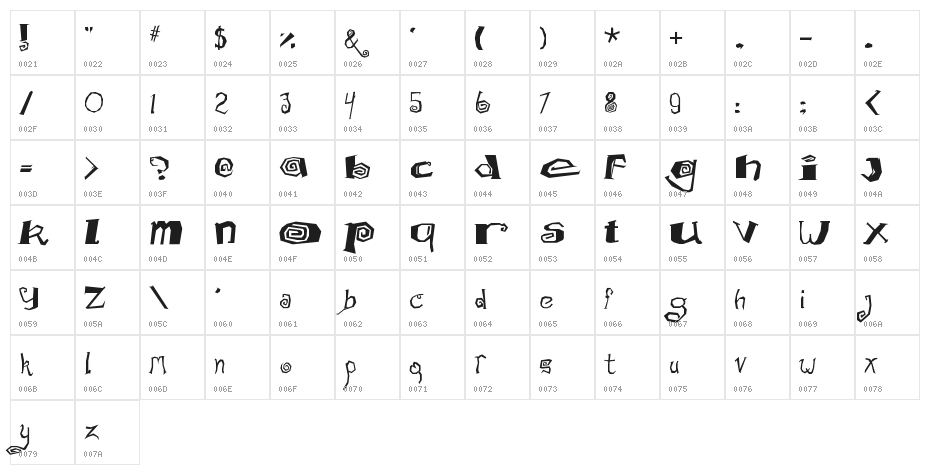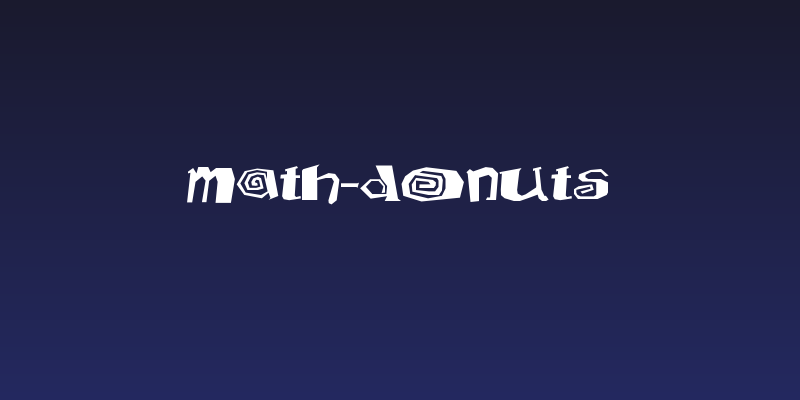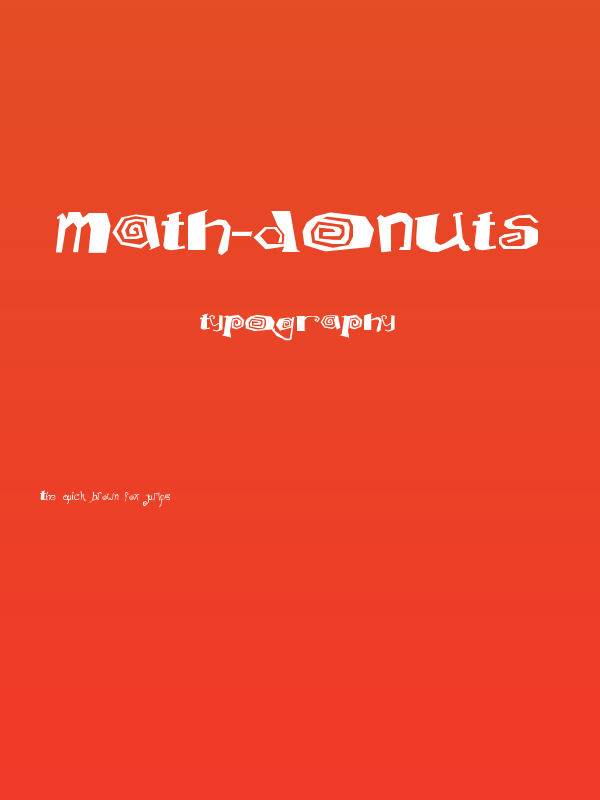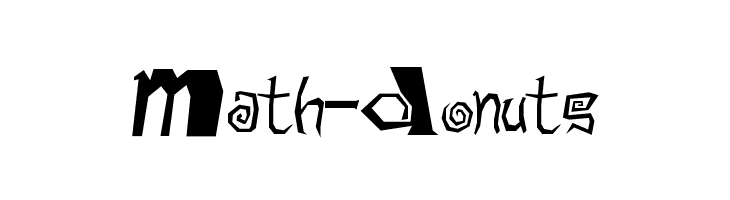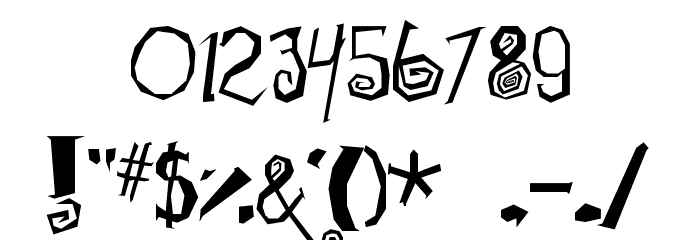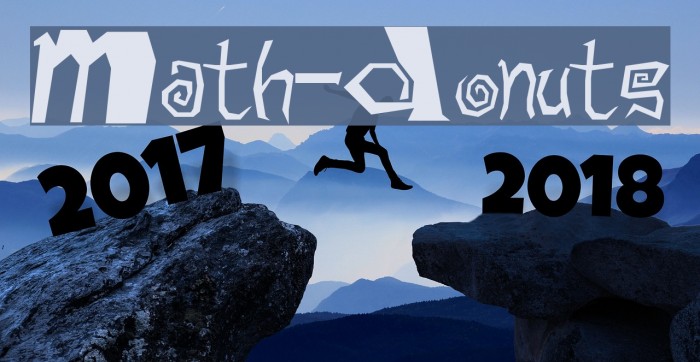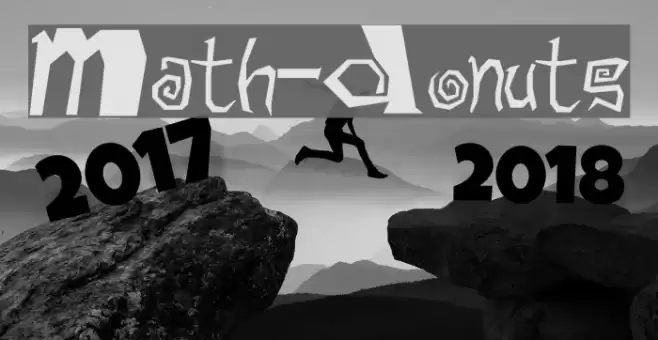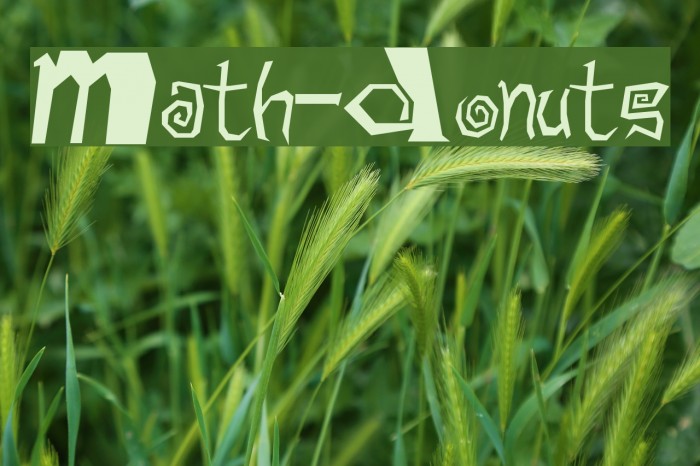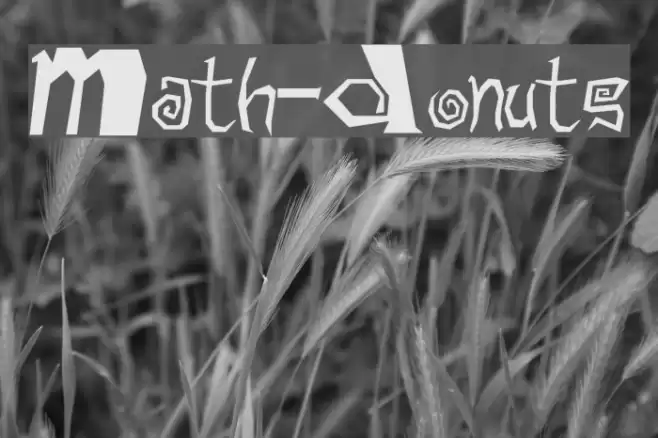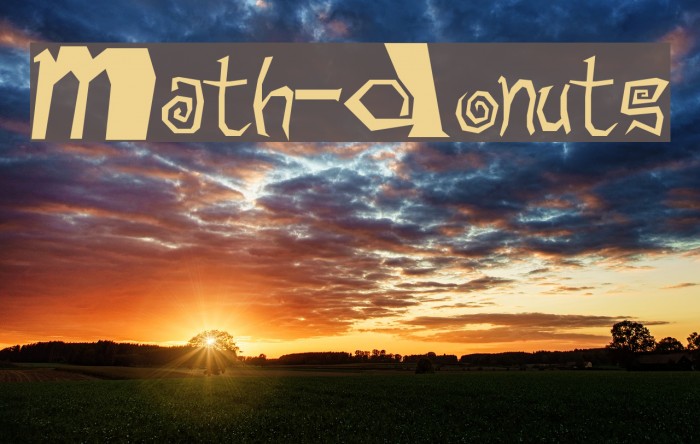
Math-Donuts Font
| Style général | Playful, Quirky, Artistic |
| Projets proposés | Ideal for children's books, playful branding, creative posters, and artistic projects. |